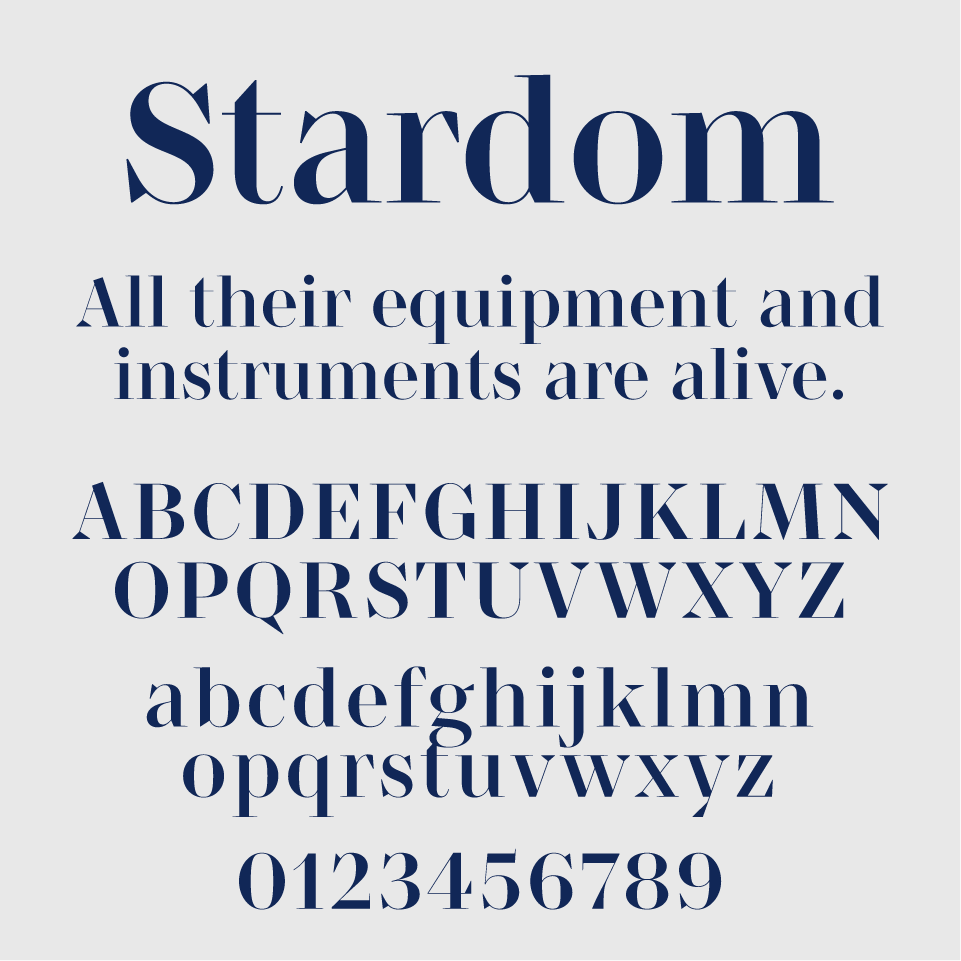
Stardomフォントは、星空のようにキラリと輝く、幻想的なムードをまとったエレガントセリフフォントです。
繊細なハイコントラストと、リズミカルに入ったユニークなカッティングが、ロマンチックな物語性を演出します。特に「S」や「a」の斜めのカットは、星のようにきらめきを放ち、上品な躍動感を生み出しています。
どこかヨーロッパのヴィンテージ映画ポスターのような美意識があり、タイトルや見出しに使うだけで“空気ごと変える”力を持っています。繊細だけどドラマティック、クラシックだけど新鮮、そんな魅力が詰まったフォントです。